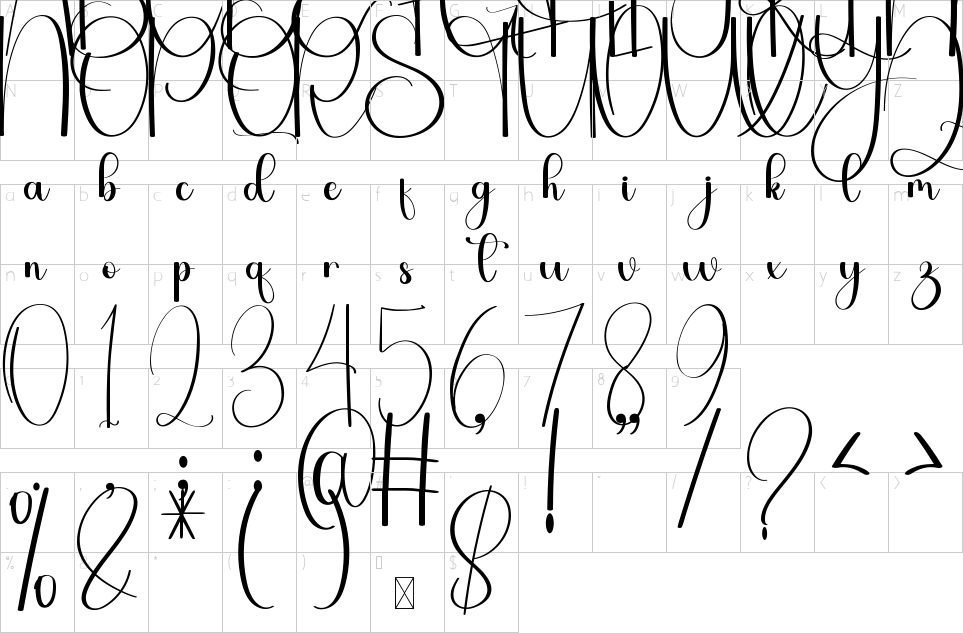
A Jumpink Font é uma fonte gráfica de estilo claro e elegante, perfeitamente adequada para aplicativos digitais e design de web. Ela foi projetada pela InermediaSTUDIO e oferece uma variedade de personalizações que vão do clássico ao moderno. Com uma fonte como esta, você pode adicionar um toque de sofisticação a qualquer projeto, seja ele para o seu site pessoal ou uma identidade visual profissional. A Jumpink Font é uma escolha ótima para aqueles buscando uma fonte limpa, versátil e gratuita. Descubra como ela pode transformar seus designs digitais e baixe-a gratuitamente para Windows e Mac.